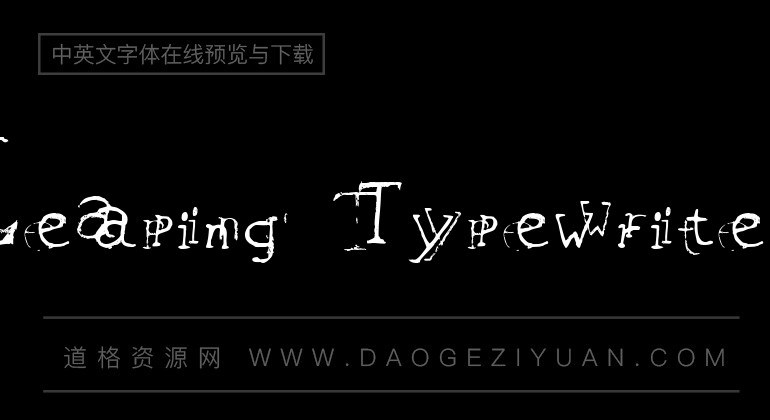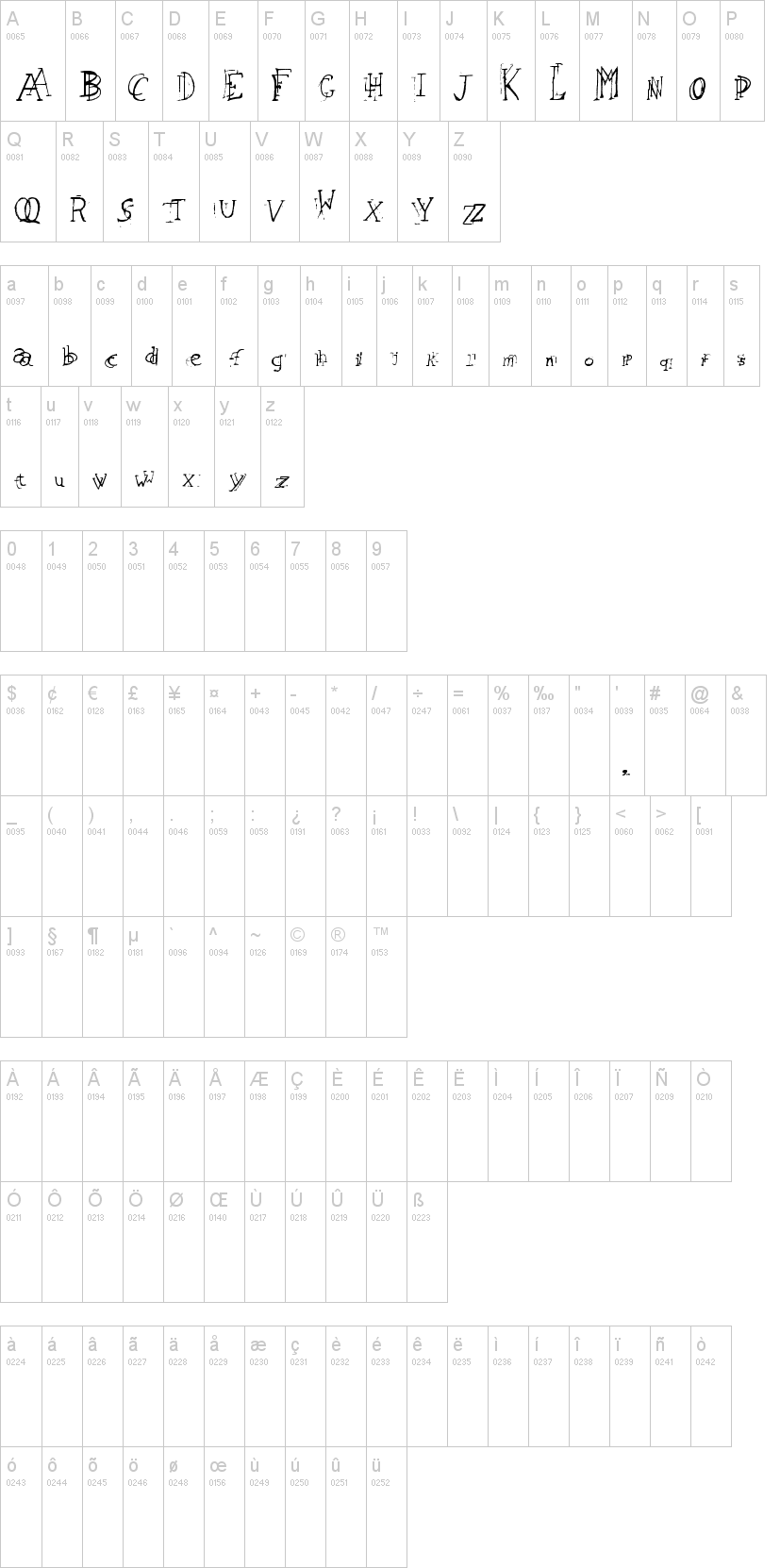
Leaping Typewriter(跳跃打字机)是一种装饰性的手写字体,它的字母看起来像是用打字机打出来的,但带有一些手写的感觉和不规则的线条。 这种字体的设计灵感来自于古老的打字机,但是在每个字母的形状上加入了一些自由的元素,使其看起来更加独特和有趣。字母间的距离也是不规则的,营造出一种不同于传统字体的美感。 因为 Leaping Typewriter 字体有很强的装饰性和个性化,通常用于海报、卡片、书籍封面等设计中,也常常被用于一些年轻人的品牌或活动中,营造出时尚、有活力的感觉。内容介绍
Leaping Typewriter是一款非常不错的手写艺术字体,具有很好的视觉感,适合于文化类的宣传设计、商业类品牌的广告和产品包装设计以及个性化文字排版等较多场景。